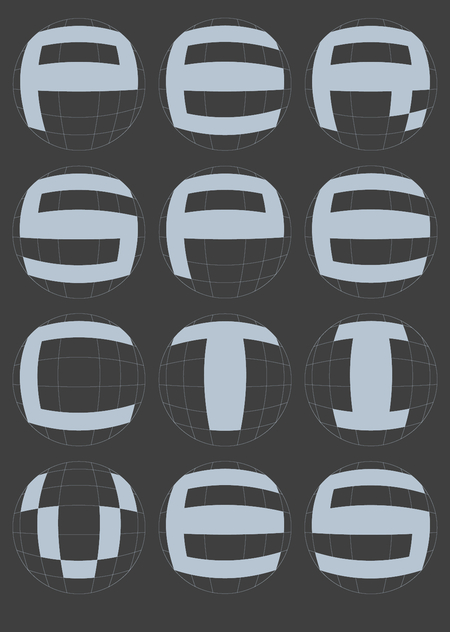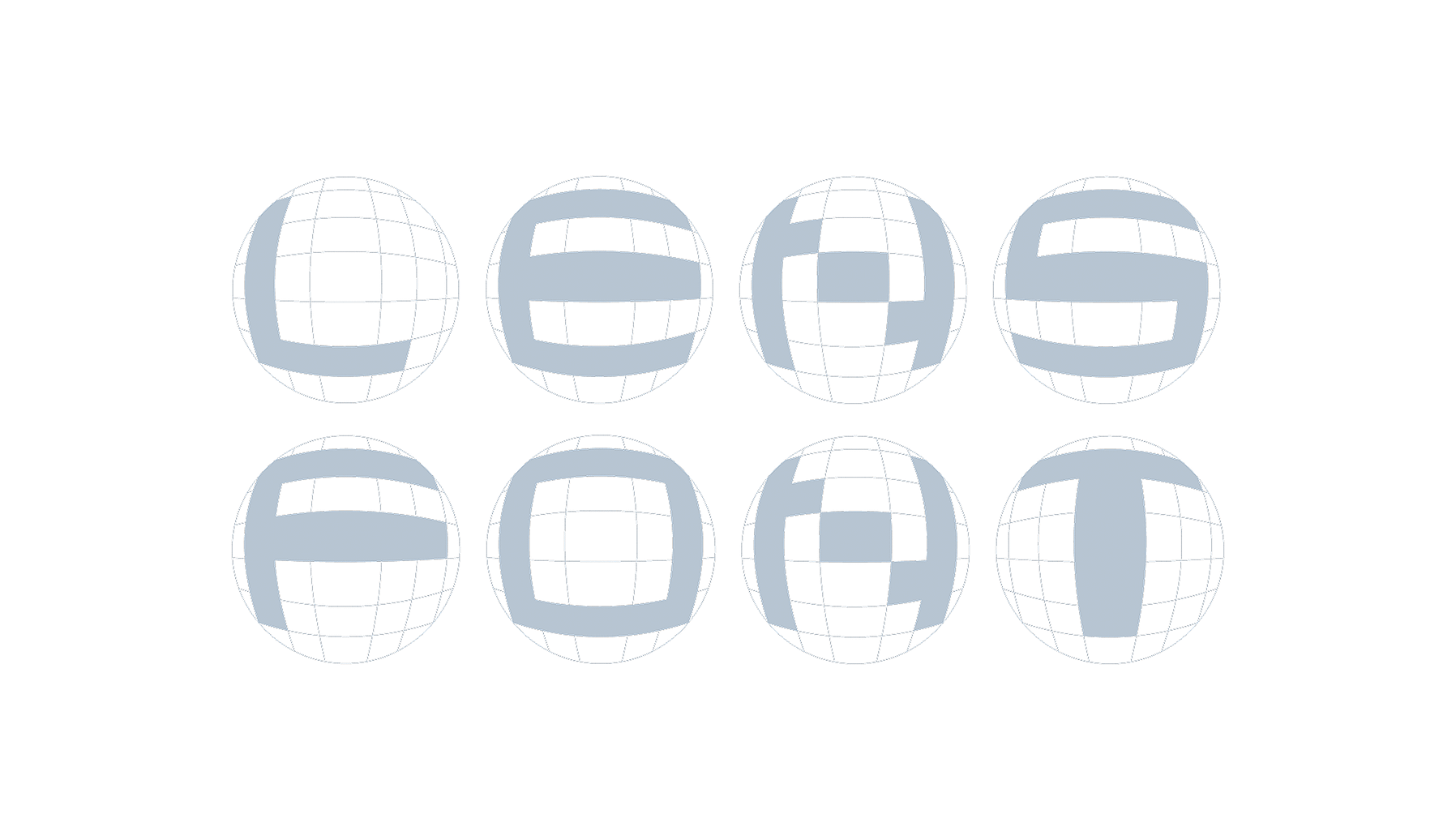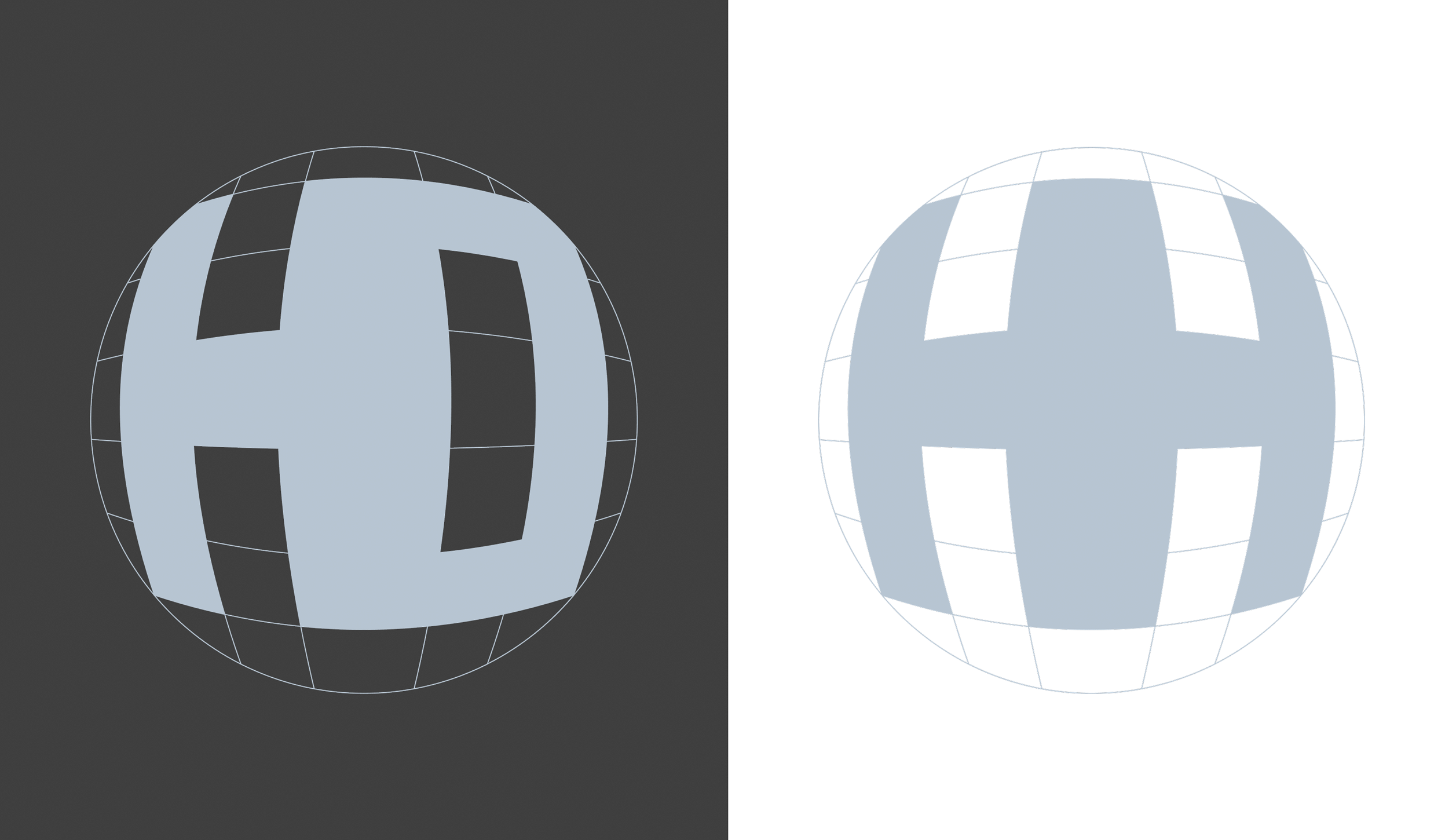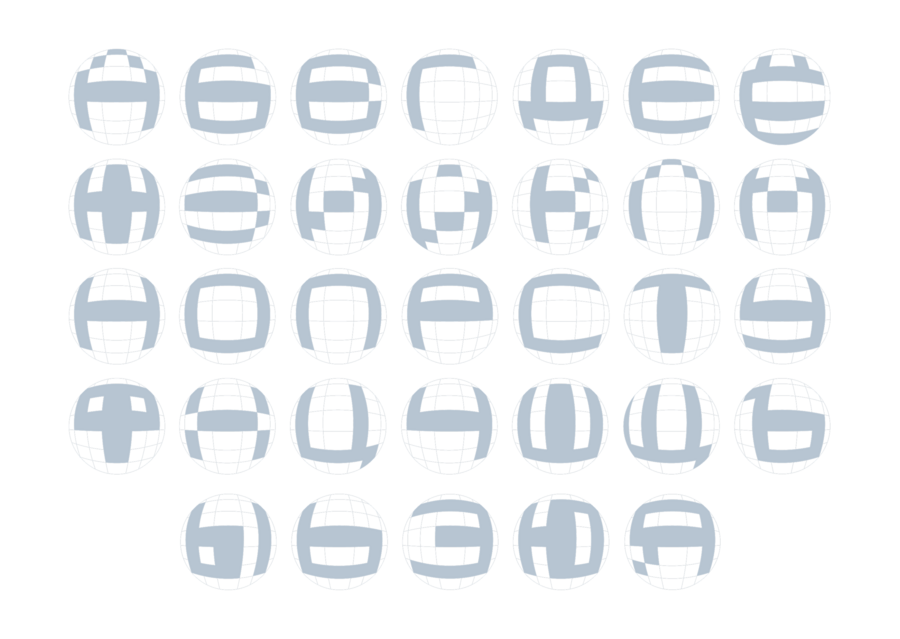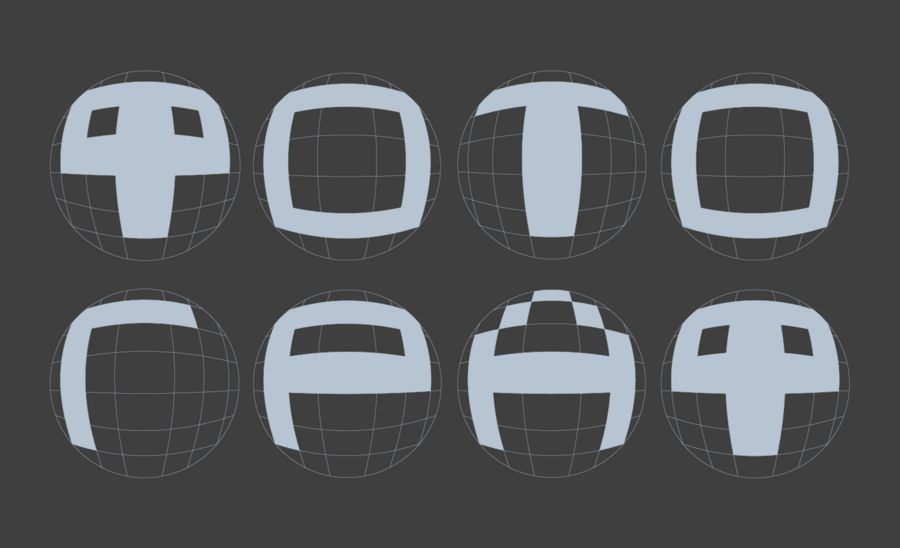
Шрифт Lens Font: айдентика выставки Perspectives
Lens Font — шрифт вдохновлённый, выпуклой перспективой линзы фотоаппарата
Perspectives — большая фотовыставка, посвящённая теме перспективы в фотографии. Её айдентика основывается на спроектированном мною шрифте Lens Font, вдохновлённым перспективой широкоугольных объектов